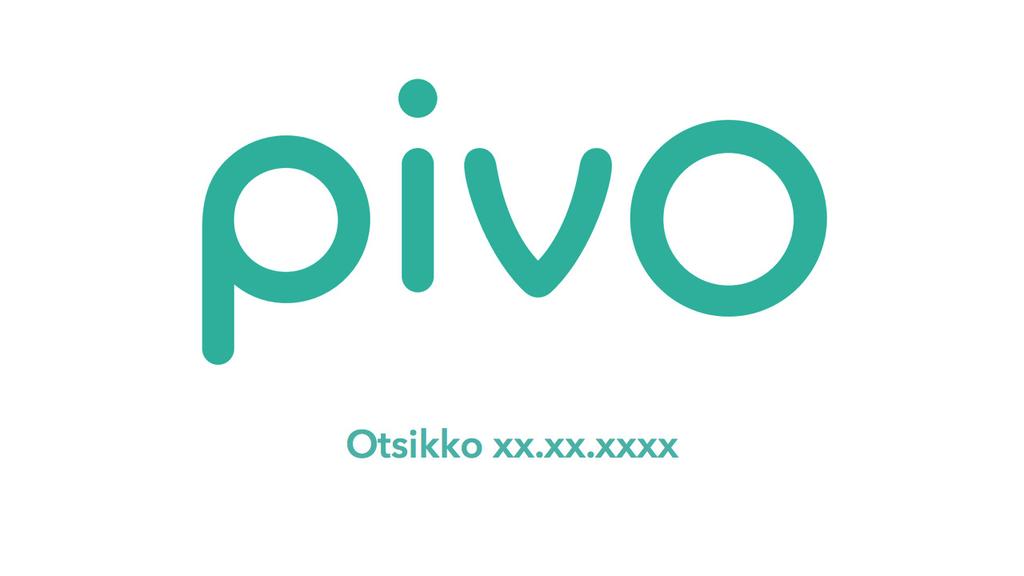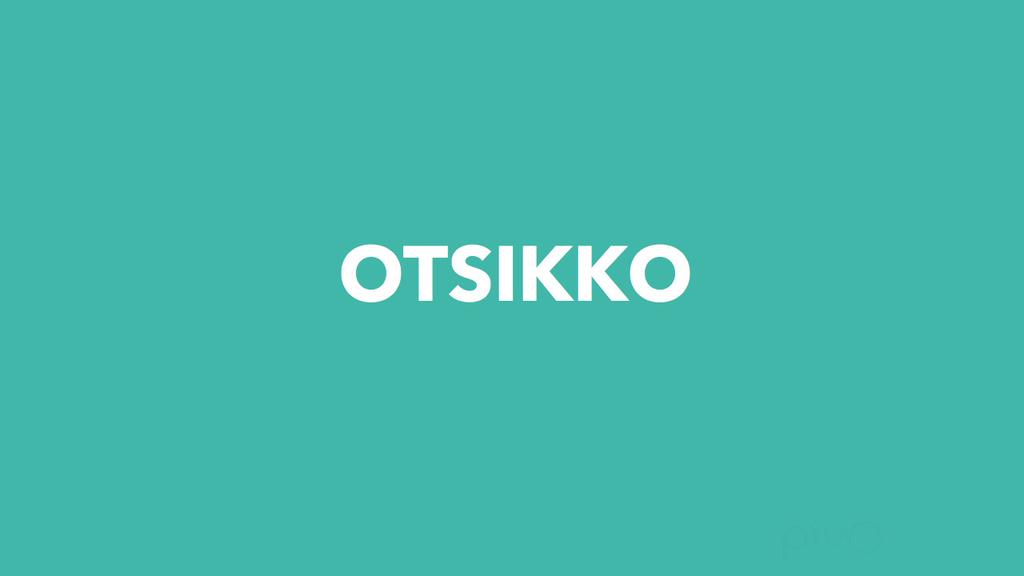
3 Pivo Logo Pivo-logo Pivon käyttöliittymä on äärimmäisen funktionaalinen, pelkistetty ja helppo. Kaikki visuaalisuus tukee tuotteen käyttäjäkokemusta. Kuten muussakin kommunikaatiossa, pyritään myös graafisessa esittämistavassa minimalismiin. Pivo on tekemisissä ihmisten omien rahojen kanssa, joten luotettavuus on erittäin tärkeää. Muoto seuraa Pivon graafisessa ilmeessä aina tarkoitusta. Logon design korostaa Pivon brändiattribuutteja: muotoiltu, uskottava, inhimillinen ja älykäs. Pivo-logosta tulee aina käyttää alkuperäistä vektoritiedostoa. Pivo-logon väri on TEAL tai negatiivi. TEAL #00C6BA R: 0 G: 198 B: 186 PMS: 326 C C: 81 M: 0 Y: 39: 0 3
4 Pivo Logon suoja-alueet Pivo-logon suoja-alue on samankokoinen kuin logon p-kirjaimen ympyrän säde. Logon suoja-alueelle ei saa asettaa muita elementtejä. Näin varmistetaan, että logolla on tarpeeksi tilaa hengittää. 4
5 Pivo Logo mustavalkoisena Pivo-logo mustavalkopainatuksessa Älä koskaan käytä harmaata versioa Pivo-logosta. Mikäli väripainatus ei ole mahdollista, Pivo-logoa käytetään täysin mustana tai mustalla pohjalla valkoisena. 5
6 Pivo Logon asettelu Pivo-logon asettelu Yhteistyökumppanien logot kuuluvat Pivo-logon oikealle puolelle. Kun Pivo-logo esiintyy jonkin muun logon kanssa yhdessä, on logojen välisen suhteen oltava tasapainoinen. Pivo ja sen yhteistyökumppanit ovat myös graafisesti samanarvoisessa asemassa. Älä koskaan aseta Pivo-logoa vinoon tai pystysuoraan. Pääasiassa Pivo-logo esiintyy yksivärisellä pohjalla. Jos se ei ole mahdollista, lado logo kuvan päälle niin, että se erottuu mahdollisimman selkeästi. 6
7 Pivo Symboli Pivo-symboli Pivon pyöreä symboli puhuu samaa muotokieltä kuin logokin. Symbolia voidaan käyttää Pivon markkinoinnissa myös toiminnallisena elementtinä sellaisena se esiintyy myös Pivon käyttöliittymässä. Kaikki Pivon tekemä markkinointi on tavalla tai toisella yhteismarkkinointia. Kun Pivo puhuu, itse symboli esiintyy aina Pivon pääväreissä. Jos markkinoinnissa näkyy yhteistyökumppanille personoitu käyttöliittymä, voi symbolin väri olla yhteistyökumppanin brändin värinen muoto säilyy aina samanlaisena. Pivo-symbolia käytetään pitämään Pivon markkinointi linjakkaana. Huom! Pivo-symboli ei korvaa Pivo-logoa! Kun symboli esiintyy markkinointiviestinnässä, on sen yhteydessä käytettävä myös Pivo-logoa. 7
8 Pivo Symbolin käyttö Pivo-symbolin käyttö Mikäli koko symboli on näkyvissä, graafiset elementit on aseteltava keskitetysti suhteessa symboliin. 8
9 Pivo Symbolin käyttö Pistä Pivo päälle. Saat meiltä älytarjouksia. Esimerkki Pivo-symbolin käytöstä yhteismainonnassa Pivo-symbolin on oltava hallitsevassa roolissa suhteessa muihin graafisiin elementteihin. 9
10 Pivo Symbolin ja logon käyttö Pivo-symbolin ja -logon käyttö Painetussa materiaalissa Pivo-logon paikka on oikeassa alakulmassa. Pivo-symboli puolestaan tulee asettaa keskelle. Pivon symboli esiintyy aina Pivon värisenä. Ainoa poikkeus tästä on, kun Pivon yhteistyökumppanille personoidun käyttöliittymän osa esiintyy markkinoinnissa. Pivo-symbolia ei käytetä ilman Pivo-logoa. Pivo-symbolin esiintyy vain yhden kerran yhdellä sivulla. Muista, että Pivo on tyylikäs tuote. Hyvä maku symbolin käytössä on erittäin toivottavaa. Liikkuvassa käytä aina Pivon logon lopputunnistetta. 10
11 Pivo Värit Primääriväri TEAL #00C6BA R: 0 G: 198 B: 186 PMS: 326 C C: 81 M: 0 Y: 39 K: 0 LIME #BBDDAA R: 187 G: 221 B: 170 PMS: 359 C C: 40 M: 0 Y: 50 K: 0 PISTACHIO #EEEEDD R: 238 G: 238 B: 221 PMS: 612 C C: 12 M: 1 Y: 12 K: 2 RUBY #FF2266 R: 255 G: 34 B: 102 PMS: 226 C C: 0 M: 100 Y: 2 K: 0 POSTIT #EEFF00 R: 238 G: 255 B: 0 PMS: 3955 C C: 4 M: 0 Y: 100 K: 0 LIGHT GREY #EAEAEA R: 234 G: 234 B: 234 C: 4 M: 2 Y: 4 K: 8 MID GREY #9F9F9F R: 159 G: 159 B: 159 C: 16 M: 11 Y: 11 K: 27 DARK GREY # R: 80 G: 80 B: 80 C: 44 M: 34 Y: 22 K: 77 11
12 Pivo Typografia Avenir Next ABCDEFGHIJKLMNOPQRSTUVWXYZÅÄÖ abcdefghijklmnopqrstuvwxyzåäö ! # $ [] ± > < Avenir Next Demibold ABCDEFGHIJKLMNOPQRSTUVWXYZÅÄÖ abcdefghijklmnopqrstuvwxyzåäö ! # $ [] ± > < Avenir Next Condensed ABCDEFGHIJKLMNOPQRSTUVWXYZÅÄÖ abcdefghijklmnopqrstuvwxyzåäö ! # $ [] ± > < Pivon typografia Pivon kirjasinleikkaus on Avenir Next. Otsikot kirjoitetaan Avenir Next Demibold leikkauksella. Rajoitetusssa tilassa voidaan käyttää myös Avenir Next Condensed leikkausta, mutta koko julkaisun linjan on oltava yhtenäinen. Pääotsikkojen värin tulee olla: TEAL #00C6BA R: 0 G: 198 B: 186 PMS: 326 C C: 81 M: 0 Y: 39: 0 12
13 Pivo Typografia Arial ABCDEFGHIJKLMNOPQRSTUVWXYZÅÄÖ abcdefghijklmnopqrstuvwxyzåäö ! # $ [] ± > < Arial Bold ABCDEFGHIJKLMNOPQRSTUVWXYZÅÄÖ abcdefghijklmnopqrstuvwxyzåäö ! # $ [] ± > < Vaihtoehtoinen typografia Mikäli Avenir Next kirjaisinta ei ole mahdollista käyttää, korvaavana kirjaisimena toimii Arial. 13